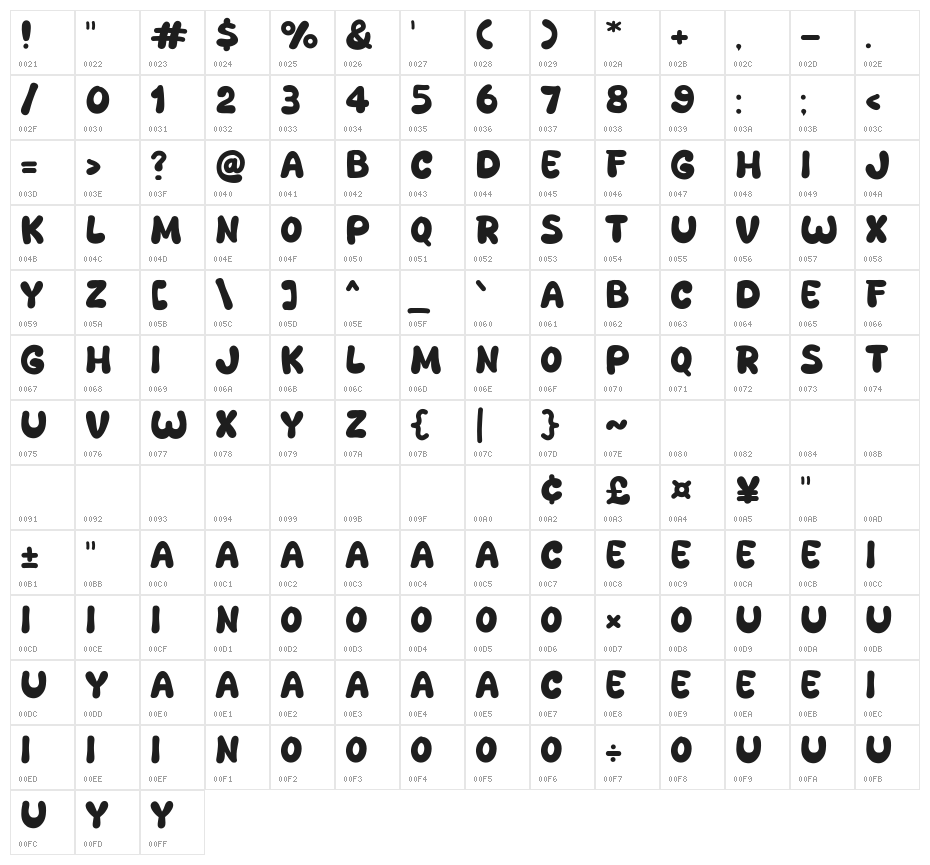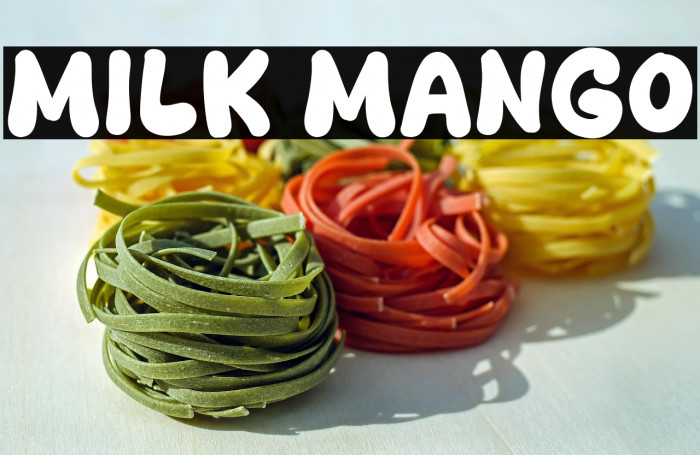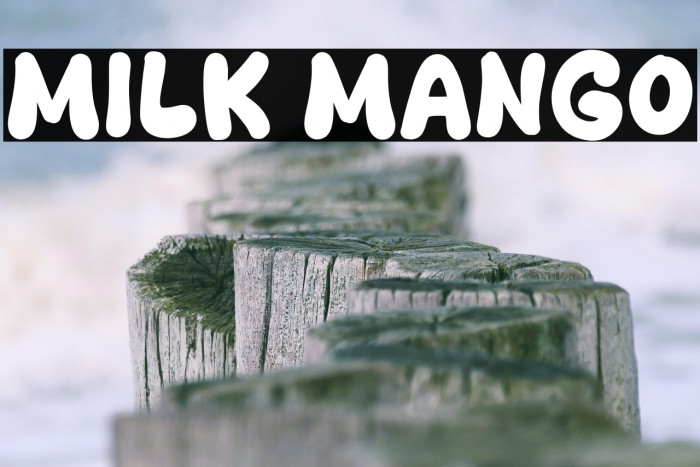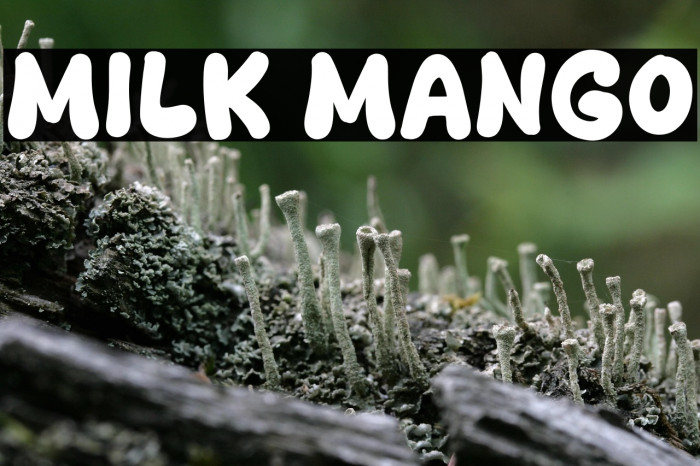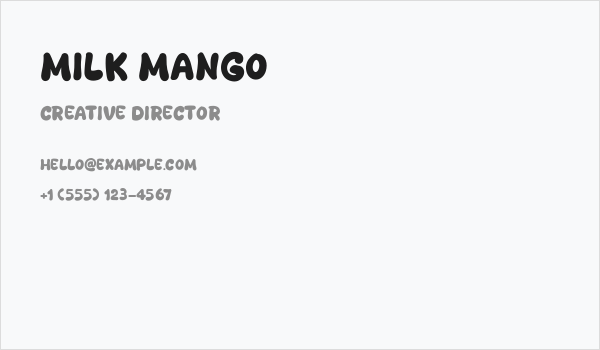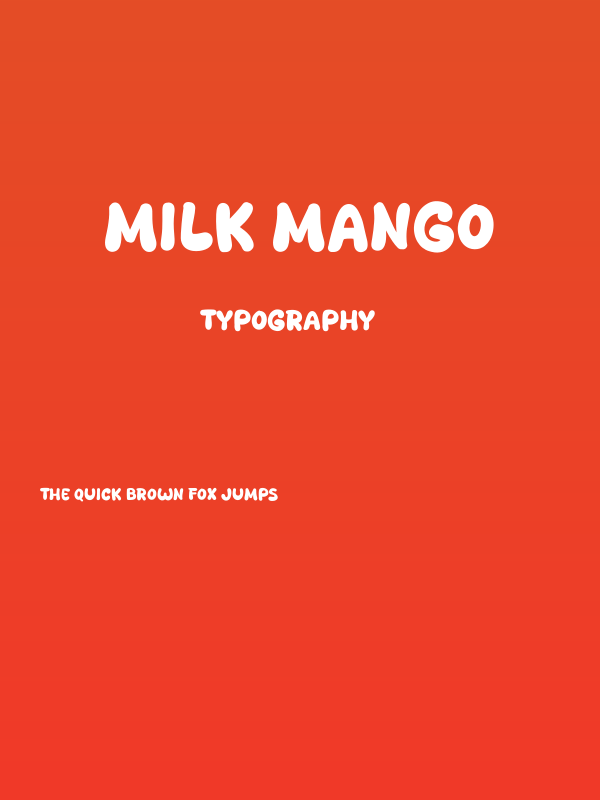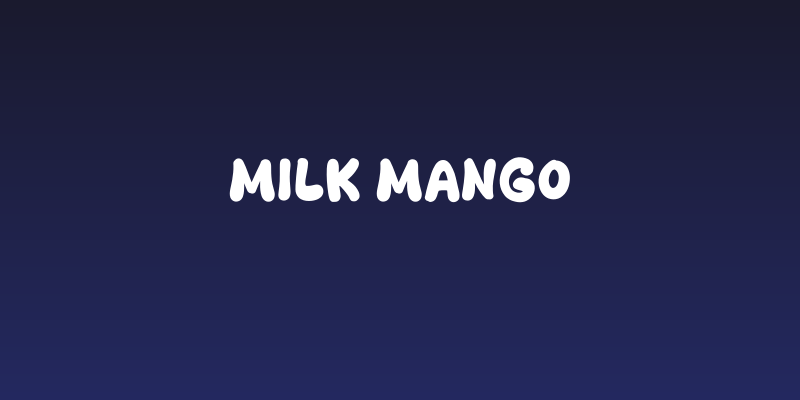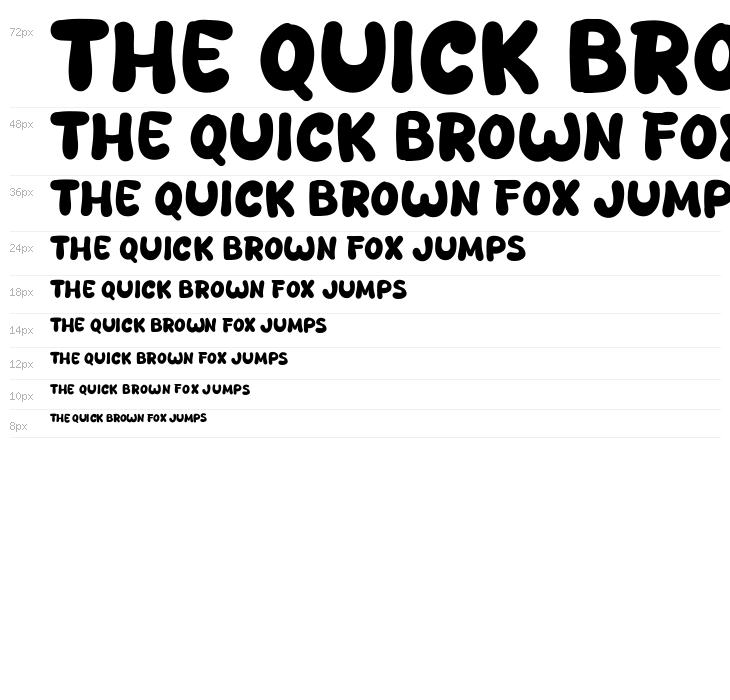
Milk Mango Font
| Общий стиль | Playful, Fun |
| Рекомендуемые проекты | Ideal for children's books, playful branding, party invitations, and eye-catching posters. |